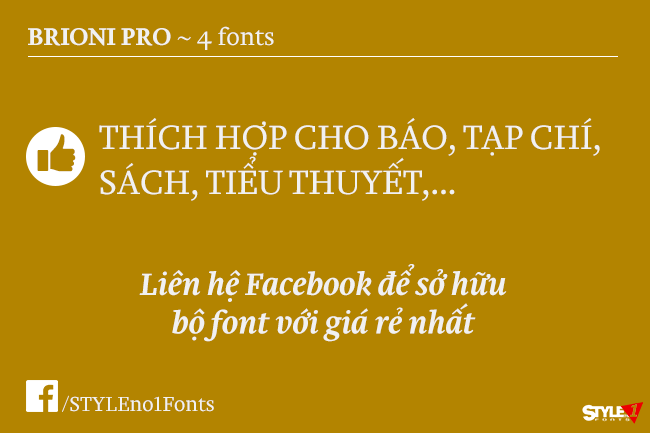
Brioni là một kiểu chữ thanh lịch, phù hợp để trình bày sách và tạp chí. Brioni được phát triển một cách tự nhiên từ việc thực hành với bút ngòi rộng, nhưng kết quả lại là sự kết hợp giữa ảnh hưởng thư pháp và sự điều chỉnh tinh tế ở các điểm cuối nét chữ.
Nhà thiết kế: Nikola Djurek
Nhà phát hành: Typotheque